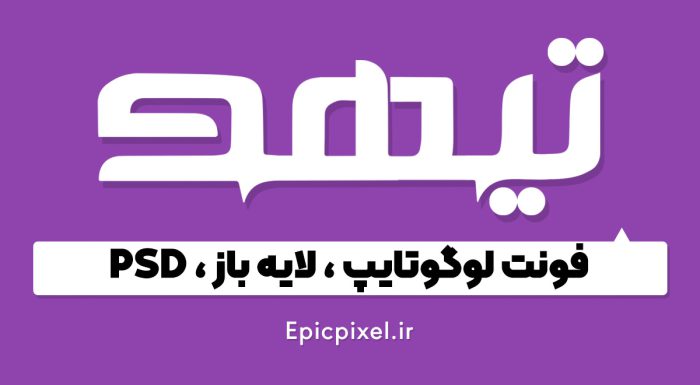
فونت لوگوتایپ تیهو فارسی
| ⭐ توضیحات | فونت تیهو یک فونت لوگوتایپ برای طراحی لوگو و تایپوگرافی بصورت کاملا لایه باز و فایل مختلف پی اس دی طراحی و آماده شده
که میتونید با استفاده از چیدن حروف و لایه ها کنار هم به اسم یا متن دلخواه خودتون برسید … |